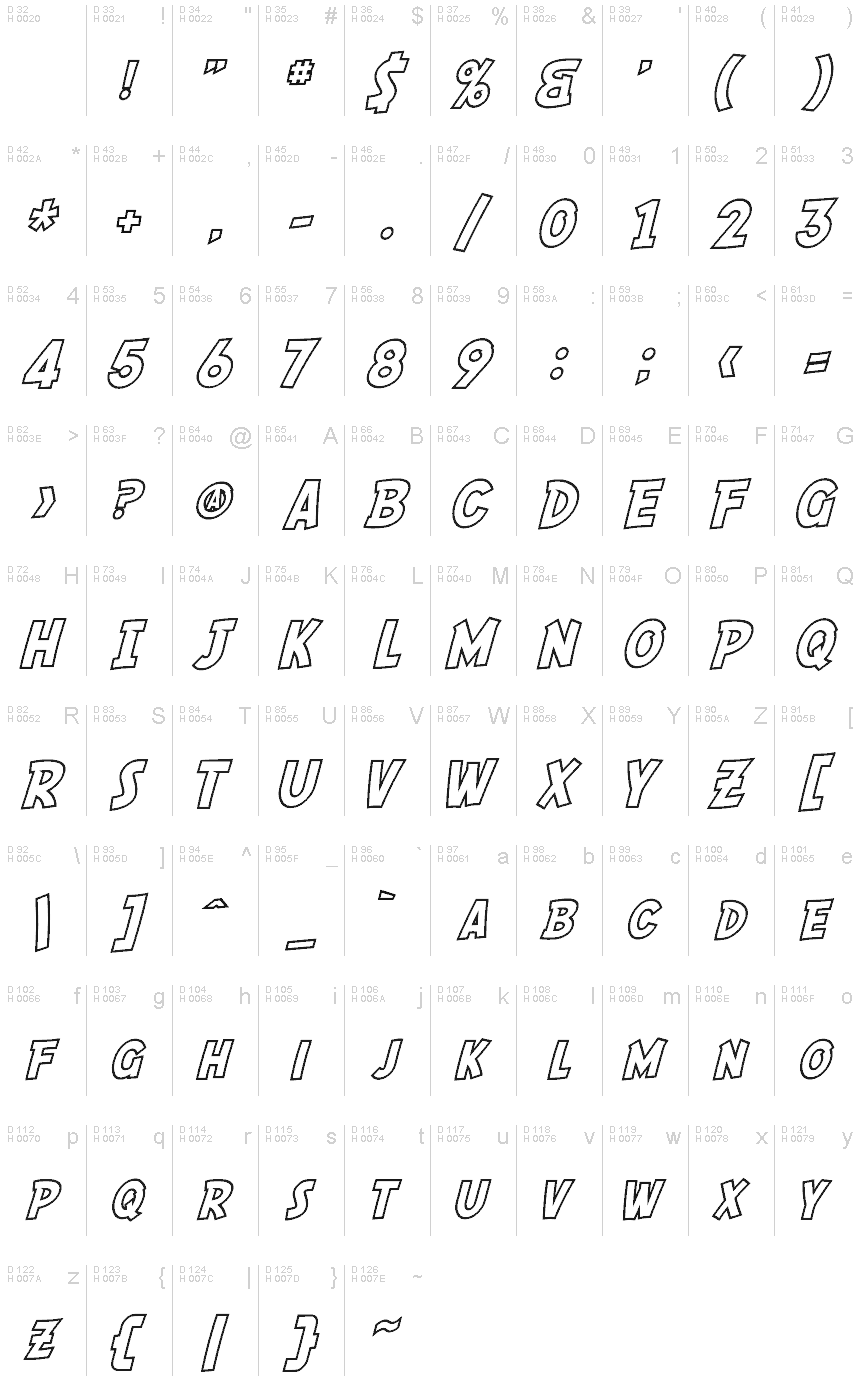
SF Comic Script Outline, wywodzący się z rodziny SF Comic Script, to dynamiczny i pełen fantazji krój displayowy stworzony przez ShyFonts Type Foundry. Dzięki swojej wyrazistej grubości, która przyciąga uwagę, font ten doskonale oddaje klimat klasycznych komiksów za sprawą konturowego stylu. Zabawne, a zarazem czytelne litery sprawiają, że jest to świetny wybór do angażowania odbiorców w różnorodnych projektach kreatywnych.
Ten konturowy wariant dodaje wszechstronności i walorów wizualnych, sprawiając, że tekst wyskakuje ze strony lub ekranu. Idealny do nagłówków, dymków w powieściach graficznych czy każdego projektu mającego na celu wywołanie radości i ekscytacji – SF Comic Script Outline sprawia, że Twój przekaz nie jest tylko czytany, ale przeżywany.
Niezależnie od tego, czy projektujesz dla mediów drukowanych, animacji czy interfejsów cyfrowych, estetyczny urok tego kroju tkwi w połączeniu nostalgii z nowoczesnym podejściem do designu. Uwolnij pełen potencjał swoich twórczych przedsięwzięć dzięki krojowi zaprojektowanemu nie tylko po to, by robić wrażenie, ale także, by wyrażać.